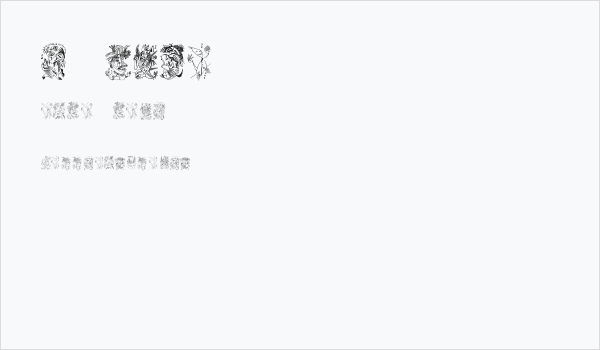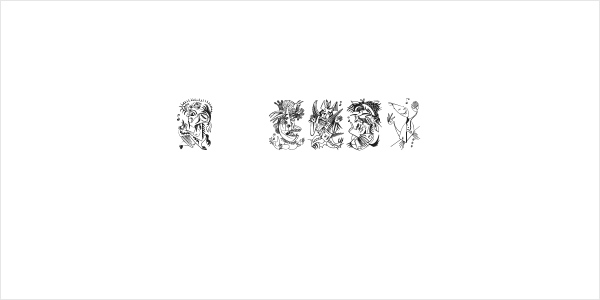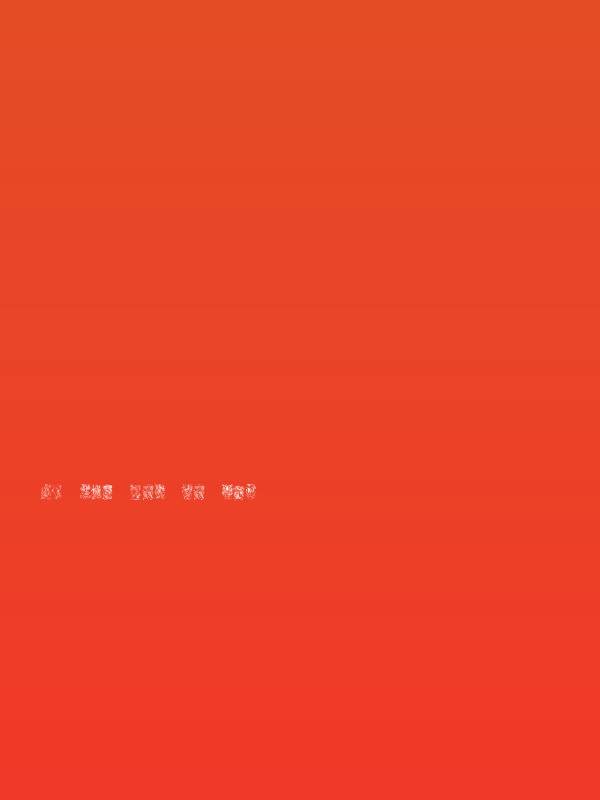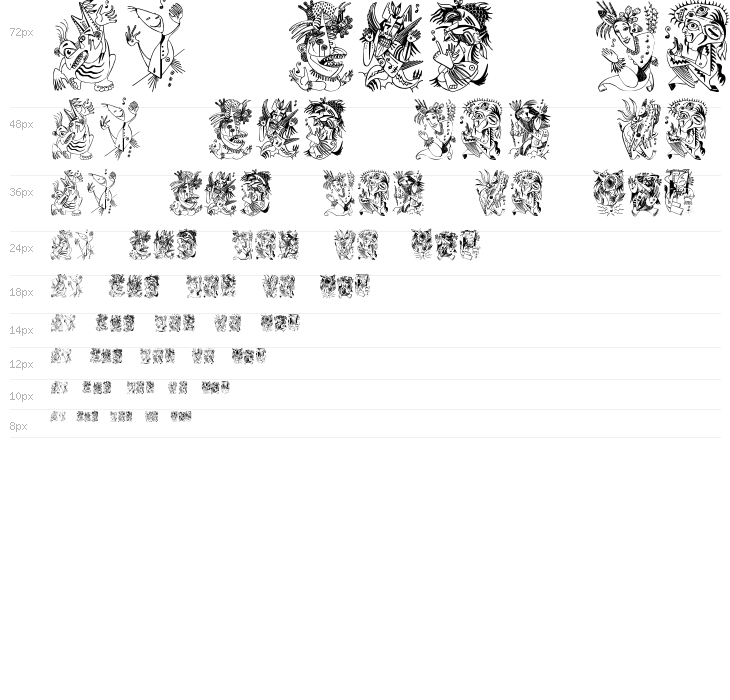
Z-Most Trickster Font
| Stile generale | Artistic, Abstract |
| Caso d'uso | Art projects, Graphic design elements |
| Progetti proposti | This set of illustrations could be used for creative projects such as art prints, posters, or graphic design elements where unique and abstract visuals are desired. |